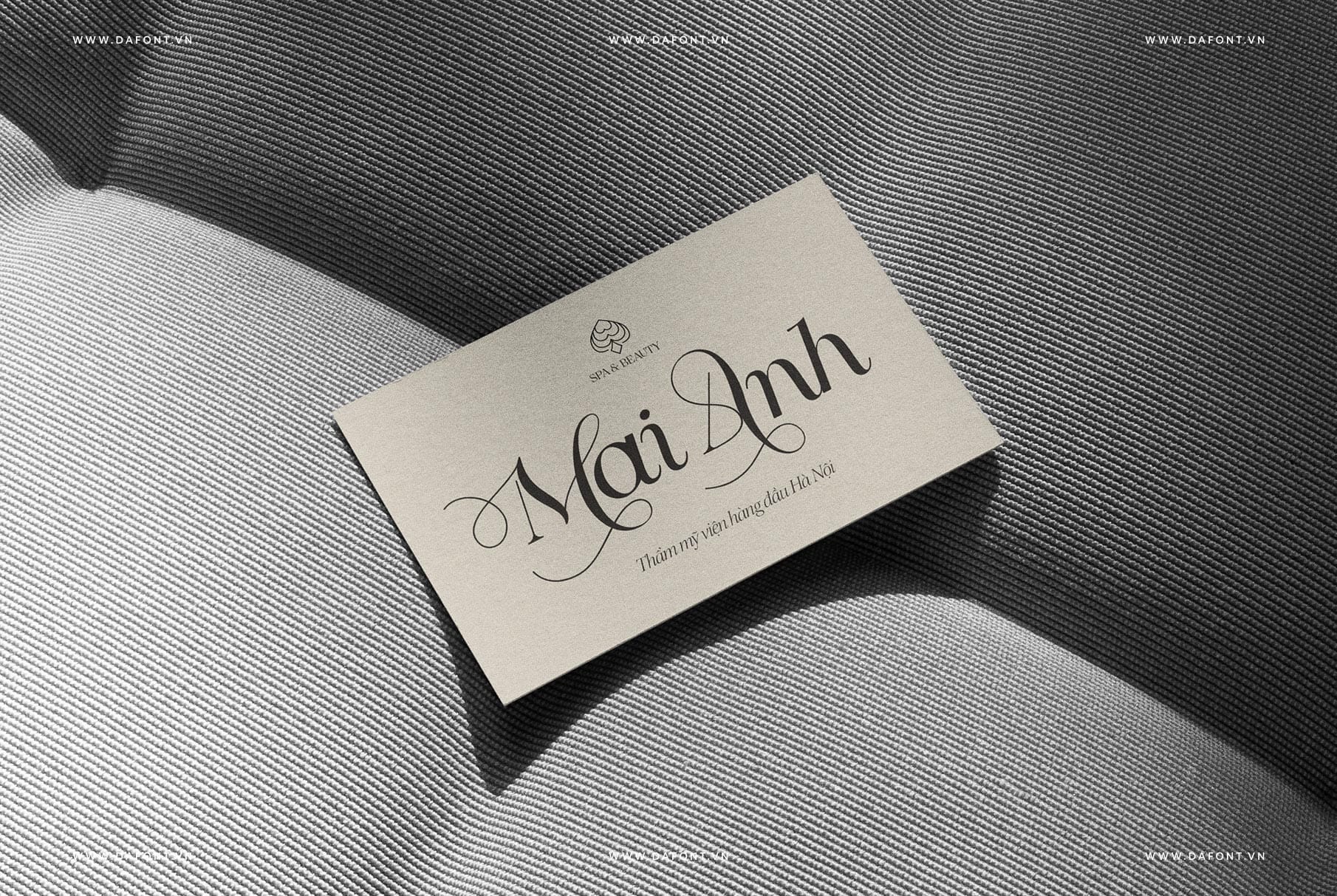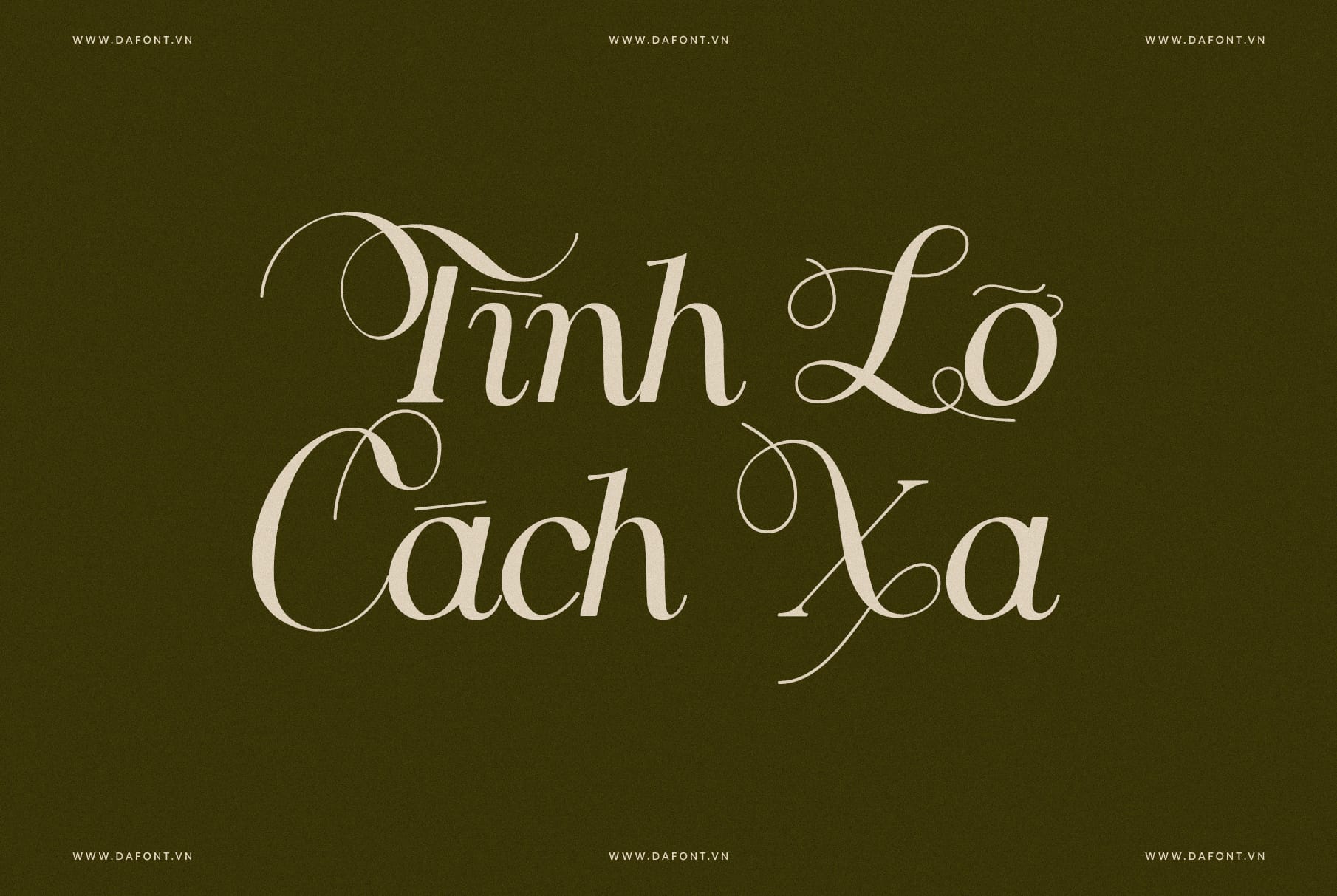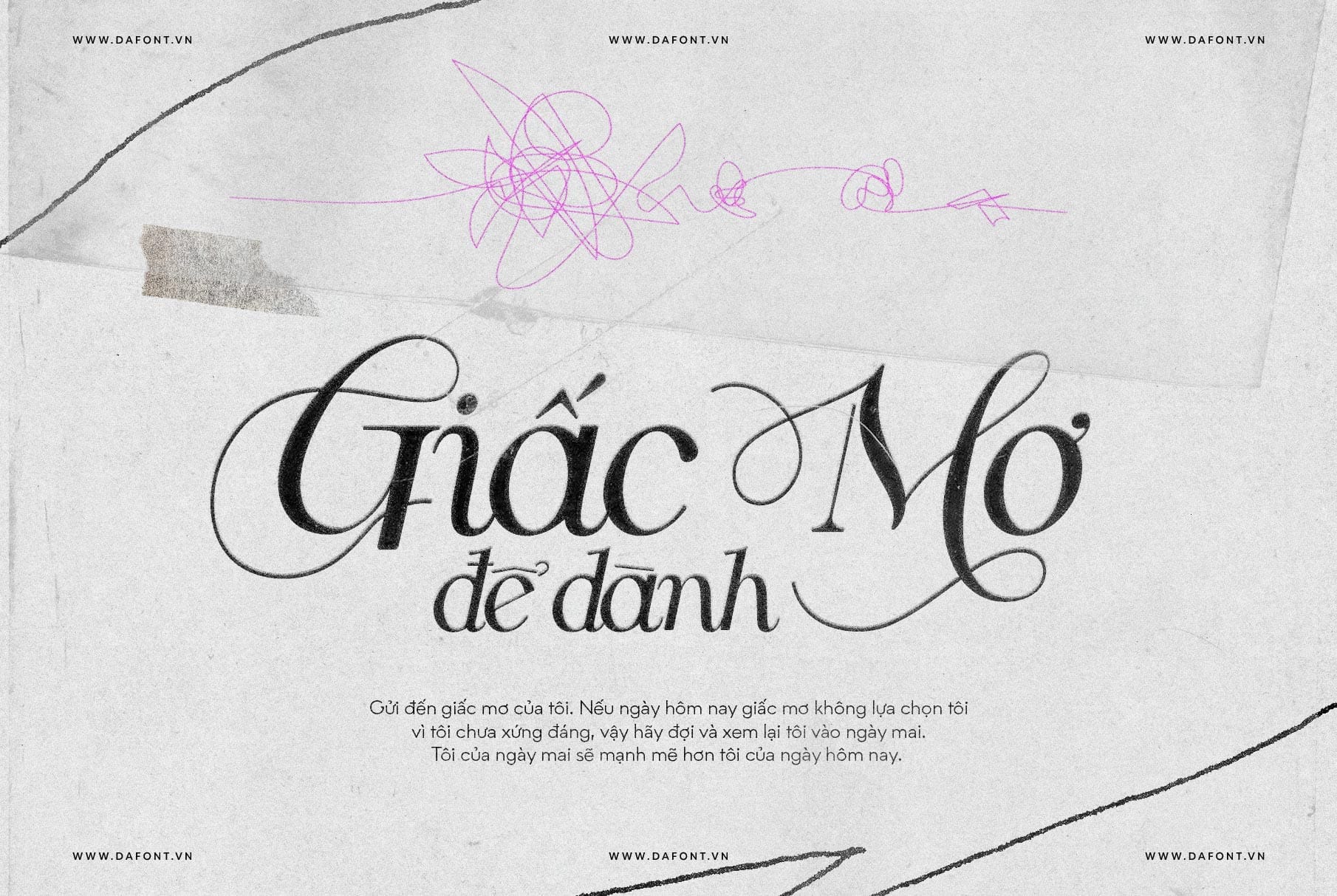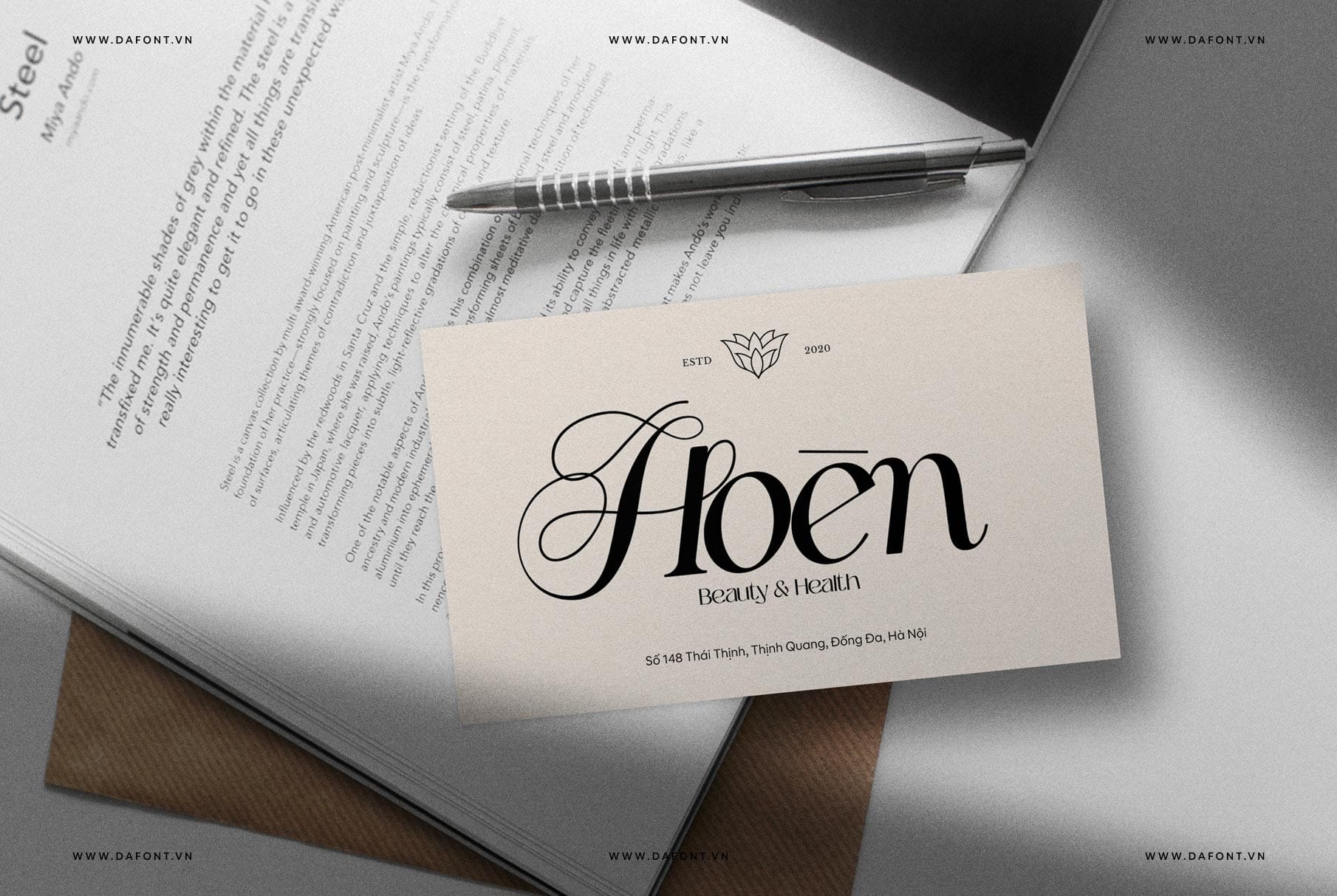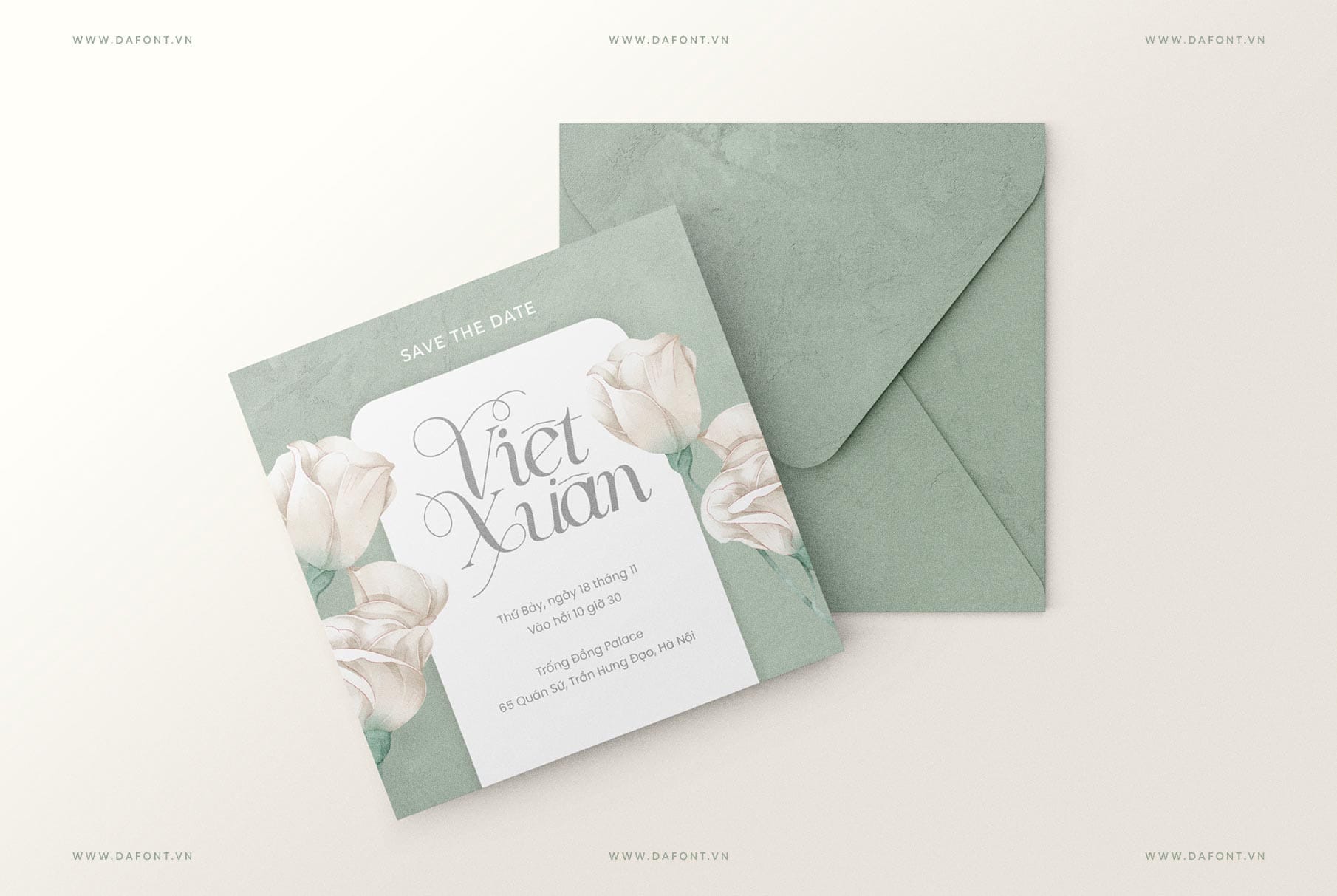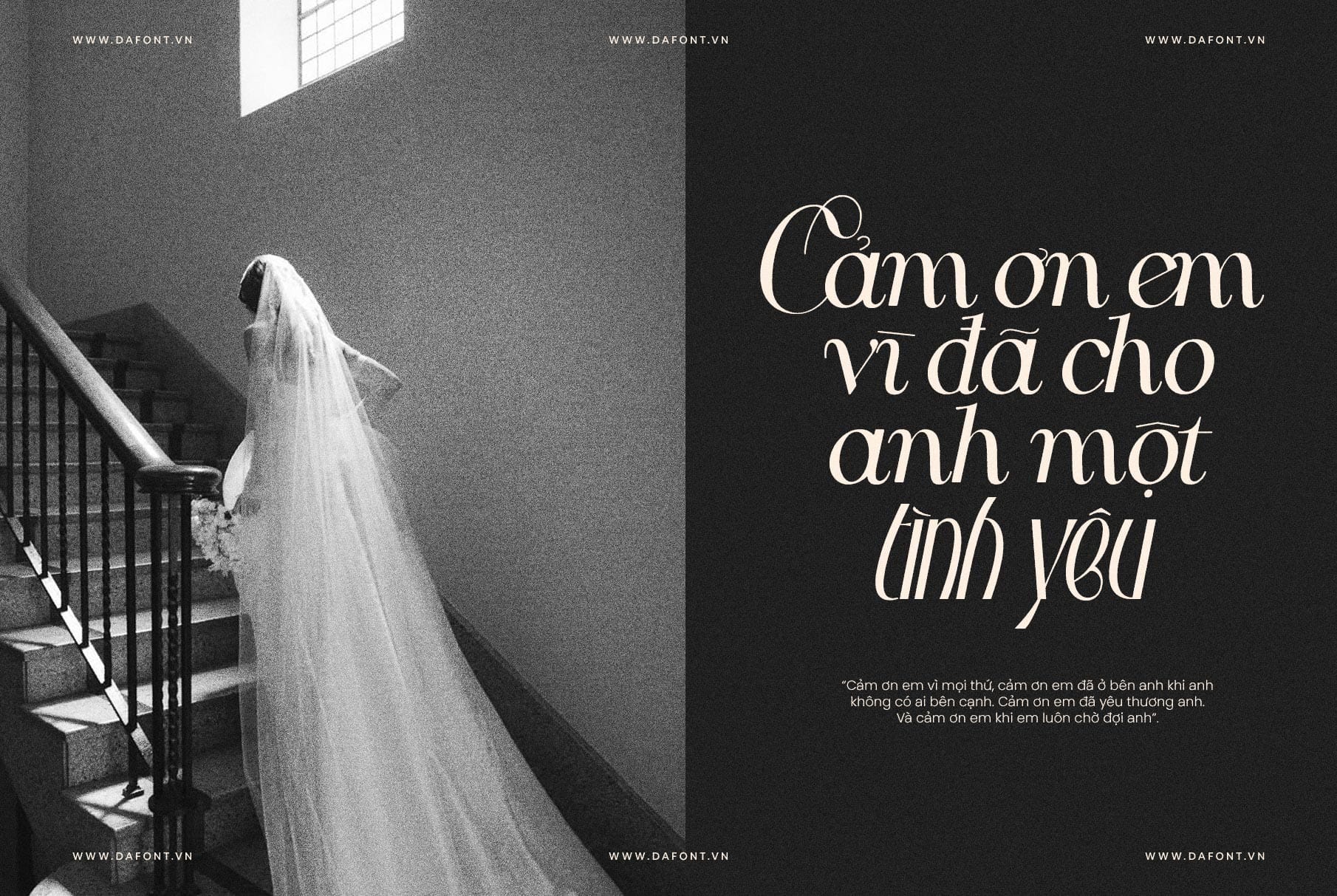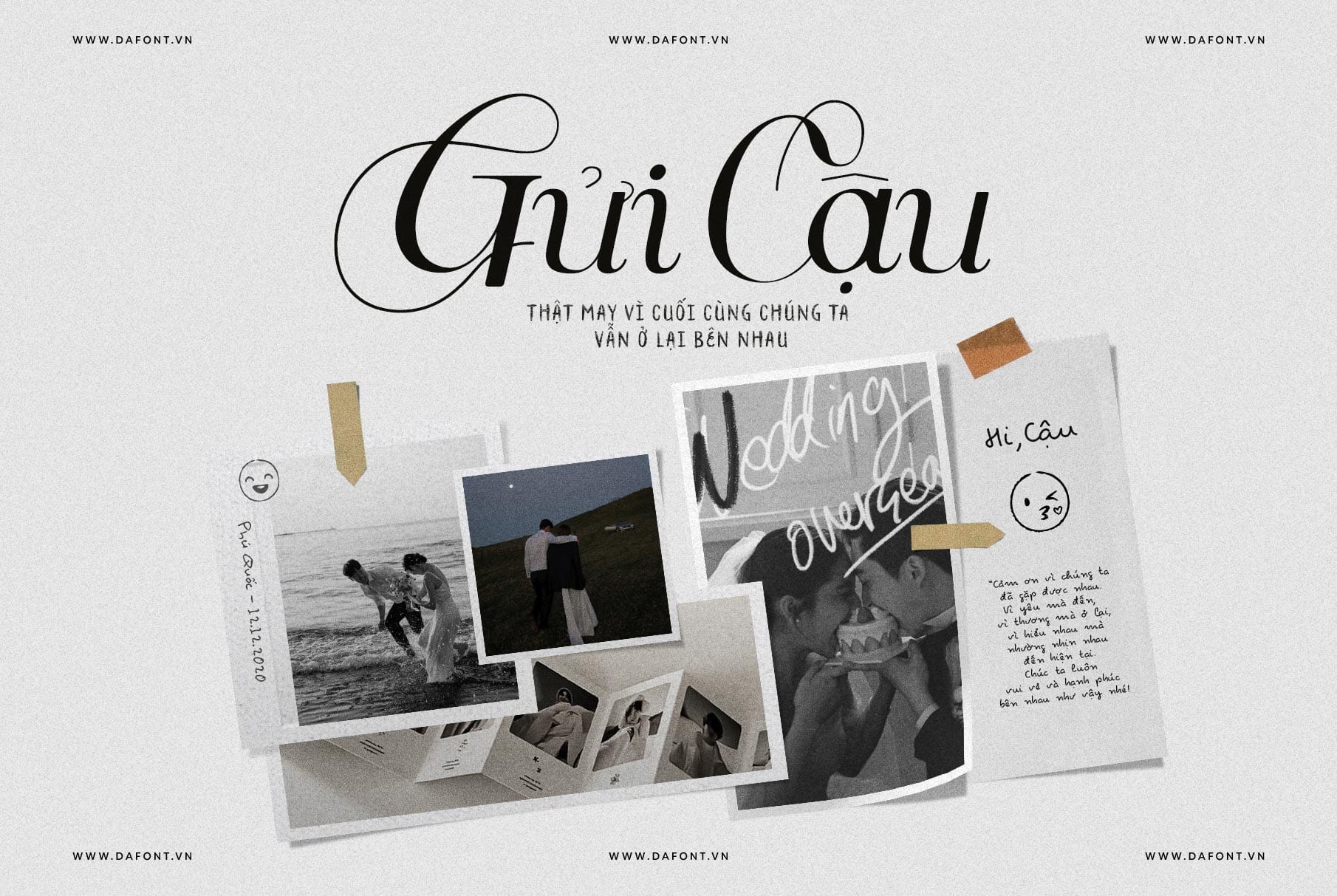
Bạn có tin rằng, đôi khi, chỉ cần một font chữ thôi cũng đủ sức mạnh để “kể” một câu chuyện, “thổi hồn” vào một thương hiệu, hay “chạm” đến trái tim người xem? Nếu bạn đang tìm kiếm “ngôn ngữ” đặc biệt ấy cho các thiết kế của mình, hãy để DFVN Noir Jolie – Font serif ligature – dẫn dắt bạn vào hành trình sáng tạo đầy cảm xúc.
Noir Jolie không chỉ là một font chữ, đó là một tuyên ngôn về vẻ đẹp vượt thời gian, là sự kết hợp hoàn hảo giữa nét cổ điển quyến rũ và phong cách hiện đại phóng khoáng. Mỗi ký tự được trau chuốt tỉ mỉ, từ những đường cong mềm mại đến những nét thẳng dứt khoát, tạo nên một bản giao hưởng thị giác đầy mê hoặc.
Chữ chép (Ligature) – Nghệ thuật “kết duyên” con chữ
Hãy quên đi những font chữ serif đơn điệu, nhàm chán. DFVN Noir Jolie mang đến một thế giới ligature phong phú, nơi các con chữ “kết duyên” một cách tự nhiên và đầy nghệ thuật. Hơn 25 chữ ghép (ligatures) được thiết kế tinh xảo, biến mỗi dòng chữ trở thành một tác phẩm calligraphy sống động, đậm chất thơ.
Noir Jolie là sự kết hợp khéo léo giữa đường cong và đường thẳng. Chữ hoa mạnh mẽ, cá tính với những nét uốn lượn, hòa quyện cùng chữ thường mềm mại, uyển chuyển. Sự đối lập này tạo nên một sức hút khó cưỡng, khiến DFVN Noir Jolie trở nên độc đáo và dễ dàng nhận diện.
DFVN Noir Jolie – Phù hợp cho nhiều thiết kế
Noir Jolie không hề “kén chọn” dự án. Cho dù bạn đang làm việc trên các dự án in ấn, thiết kế đồ họa, hay các ấn phẩm kỹ thuật số, Noir Jolie đều có thể đáp ứng mọi nhu cầu của bạn như:
- Xây dựng thương hiệu cá nhân/doanh nghiệp (Branding): Tạo dựng hình ảnh sang trọng, tinh tế và đáng nhớ.
- Thiết kế website và giao diện người dùng (Web Design & UI): Nâng cao trải nghiệm đọc, thu hút và giữ chân người dùng.
- Ấn phẩm truyền thông (Print Materials): Biến hóa brochure, tạp chí, sách báo trở nên đẳng cấp và chuyên nghiệp.
- Marketing và quảng cáo (Marketing & Advertising): Gây ấn tượng mạnh mẽ, thu hút sự chú ý trong các chiến dịch truyền thông.
- Thiệp mời, thiệp cưới và quà tặng (Stationery & Gifts): Thể hiện sự trân trọng, tinh tế và gu thẩm mỹ độc đáo.
Hãy để DFVN Noir Jolie “kể chuyện” thiết kế của bạn
DFVN Noir Jolie được chăm chút tỉ mỉ qua quá trình Việt hóa, với sự tối ưu hóa cẩn thận cho từng dấu và ký tự. Kiểu chữ này được thiết kế độc đáo với hai kiểu dấu khác biệt, tăng cường khả năng sử dụng và linh hoạt hơn. Đồng thời, một số chữ cái in hoa cũng được điều chỉnh tinh tế, làm tăng thêm sự hài hòa và thẩm mỹ cho kiểu chữ.